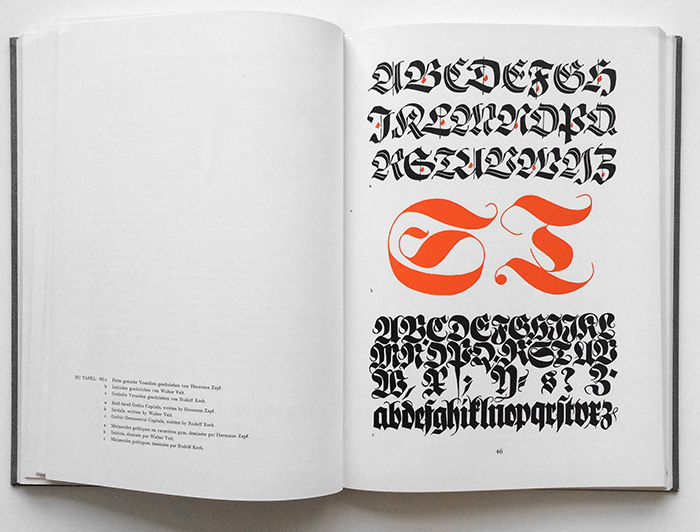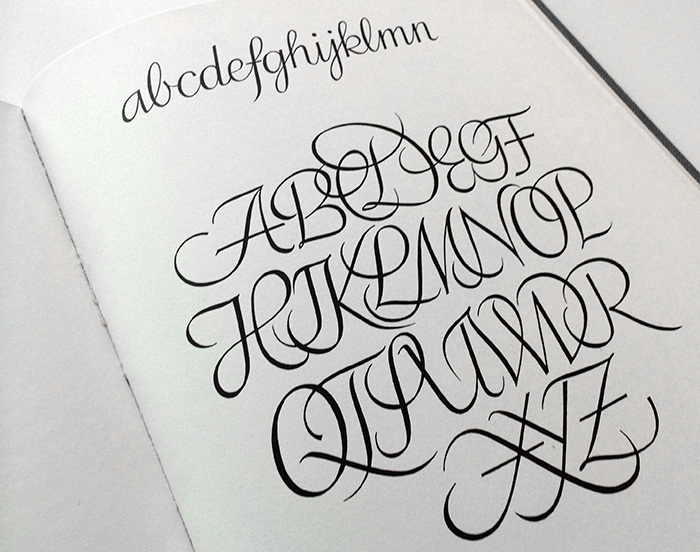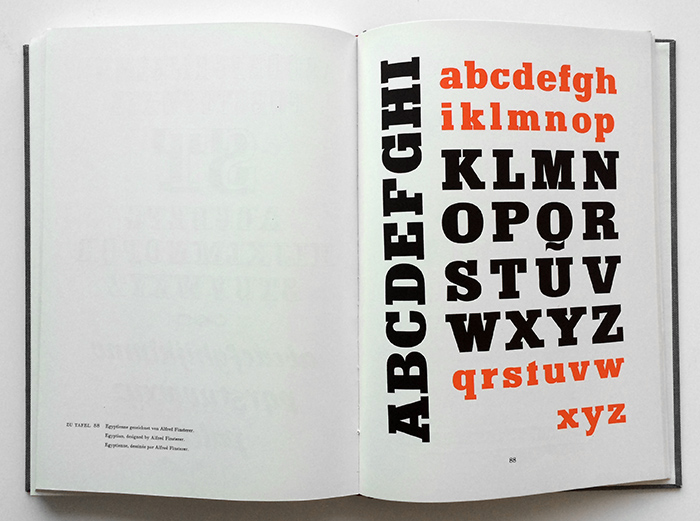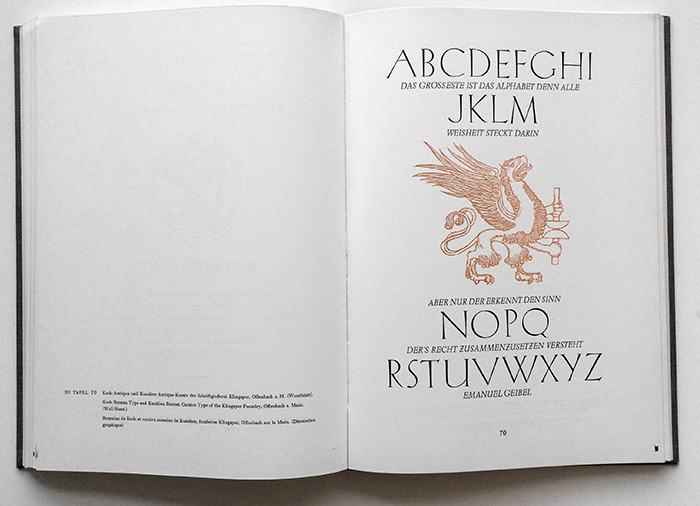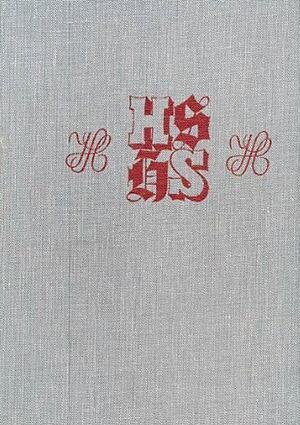
Hoffmanns Schriftatlas erschien 1930 und wurde in Zusammenarbeit mit Albert Bruckner, Max Hertwig und Rudolf Koch herausgegeben. 1952 erschien die hier vorliegende, überarbeitete und erweiterte Fassung, die von Alfred Finsterer herausgegeben wurde. Das recht großformatig angelegte Werk (circa 24×34 cm) enthielt nun 92 Tafeln mit Schriftproben sowie 14 Seiten Druckschriftenübersichten. Die Tafeln zeigen den Formenreichtum aus 2000 Jahren lateinischer Schrift in Form von Buchseiten, gesetzten Schriftmustern und kalligrafischen Arbeiten. Am Ende des Buches sind zusätzlich Satzschriften der wichtigsten Gießereien der Zeit im deutschsprachigen Raum in 12 Punkt abgesetzt.
Tafelregister:
- Aethelwold, Benedictionale
- Andreae, Hieronymus
- Antiphonar von Plantin
- Antiqua
- Antiqua-Kursiv
- Ariston
- Augustinus, De Civitate
- Augustinus, De Trinitate
- Baemler, Johann
- Balzac-Pinseschrift
- Barbedor, Louis
- Baskerville-Antiqua
- Bastard
- Bauersche Gießerei
- Benedictionale des Hl. Aethelwold
- Bentele, Ernst
- Berthold A.G., H.
- Bodoni, Giambattista
- Bodoni-Antiqua
- Boehland, Johannes
- Boissens
- Bourgoin
- Bremer Presse
- Buchkursiv
- Bunz, Ernst
- Cancellaresca
- Caslon
- Caslon-Antiqua
- Caslon-Kursiv
- Castillione, Giovanni Antonio
- Chambre, Jean de la
- Civilité, Lettre de la
- Colard Mansion
- Cresci, Giovanni Francesca
- Deberny & Peignot
- Delphin
- Deutsche Kanzleischrift
- Didot, Firmin
- Diethelm-Antiqua
- Diurnale von Schönsperger
- Dürer, Albrecht
- Egyptienne
- Ehrenpforte für Maximilian I.
- Eidenbenz, Hermann
- Etienne, Antoine
- Euphorion
- Evangeliar aus der Abtei Fécamp
- Evangeliar aus Prüm
- Feyerabend, Sigismund
- Finsterer, Alfred
- Folchard Psalter
- Forum
- Fraktur
- Froschauer, Christoffel
- Funk, Eugen
- Fust und Schöffer
- Futura
- Garamond-Antiqua
- Gavotte
- Gilgengart
- Gilgengart-Fraktur
- Gotische Abwandlungen
- Graduale
- Granjon, Robert
- Graphique
- Gras serré Italique
- Griffo, Francesco
- Grotesk
- Gutenberg, Johannes
- Haasche Schriftgießerei A.G.
- Hadank, A. H. W.
- Halbunzialis
- Hammer, Victor
- Hartmann, Schedelsche Weltchronik
- Heinrichsen, Friedrich
- Historienbibel
- Höfer, Karlgeorg
- Ideal-Antiqua
- Jessen
- Initiales Ombrées
- Italique
- Kapitalis quadrata
- Kapitals, römische
- Karolingische Minuskel
- Keidel, Karl
- Kelmscott-Press
- Kilian, Hans
- Kleistfraktur
- Kingspor, Gebr.
- Koberger, Anton
- Koch, Rudolf
- Koch-Antiqua
- Kumlien, Akke
- Kumlien-Antiqua
- Künstlerschreibschrift, halbfette
- Kursiv
- Lauber, Diebold
- Lectionarium Missae
- Legende
- Leins, Margarete
- Lenz, Max
- Manutius, Aldus
- Marées-Gesellschaft
- Mediaeval
- Michelangelo-Antiqua
- Missaleschrift
- Morris, William
- Neudorfer, Johann
- Normande
- Noten
- Notentitel
- Numeister, Johannes
- Ornata
- Orpheus-Antiqua
- Palatino
- Pinselschrift
- Plantin, Christoph
- Post, Hebert
- Post-Antiqua und -Versal
- Post-Fraktur
- Post-Mediaeval
- Profil
- Prüm. Evangeliar
- Ratdold, Erhard
- Reiner, Imre
- Renner, Paul
- Römische Kapitalis
- Rotunda oder Rundgotisch
- Rustica
- Salto
- Schadow
- Schneidler, Ernst
- Schönsperger, Johannes
- Schwabacher
- Scrittore, Il perfetto
- Simons, Anna
- Smith, Duncan
- Spemann, Rudo
- Staatliche Akademie Stuttgart
- Stahlstich
- Stempel A.G.
- Textur
- Theuerdank
- Tiemann, Walter
- Trump, Georg
- Unzialis
- Veit, Walter
- Vergilius, Georgica und Aeneis
- Vulgata
- Wahlaffiche aus Pompeji
- Weber, C.E.
- Weiss, E.R.
- Wiegand, Willi
- Wilke, Martin
- Wolf, Jacob
- Wyss, Urban
- Zapf, Hermann
- Zentenar-Fraktur
Untertitel: Ausgewählte Alphabete und Anwendungen aus Vergangenheit und Gegenwart
Autor(en): Alfred Finsterer (HRSG.)
veröffentlicht: 1952
Verlag: Verlag Julius Hoffmann Stuttgart
Sprache: deutsch, englisch, französisch